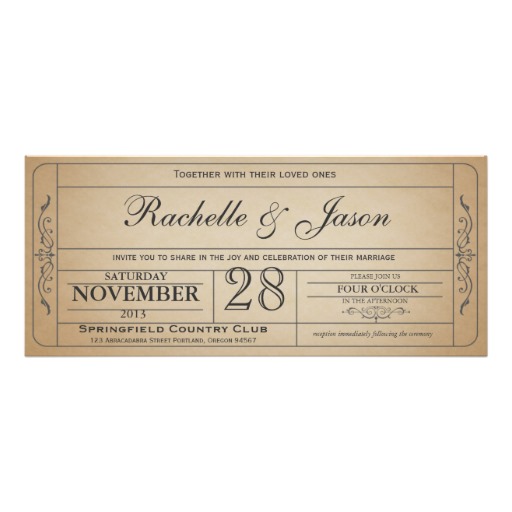
Welcher Font ist das ? Benötige allerdings nur die Zahlen!
ich habe hier eine Beispielgrafik mit einer Zahl. Diesen Outline-Font konnte ich allerdings bislang nicht identifizieren.
Weiß jemand um felchen Font es sich handeln könnte?
Möglichweise händisch der Graphik auf Basis einer Garamond hinzugefügt? Hast du mehr Angaben zur Herkunft, ggf. sogar die ganze Graphik?
Hier ist die gesamte Grafik, diese wurde mir allerdings zugeschickt, habe daher weder Zeit- noch Herkunftsangaben.
AH. 1000 Dank. Wie bist du heran gegangen?
ich wusste das es eine Goudy Handtooled gibt und nachdem es die nicht war,
habe ich dann bei myfonts einfach die restlichen suchtags ausprobiert.
"prismatic" brachte dann das passende ergebniss.